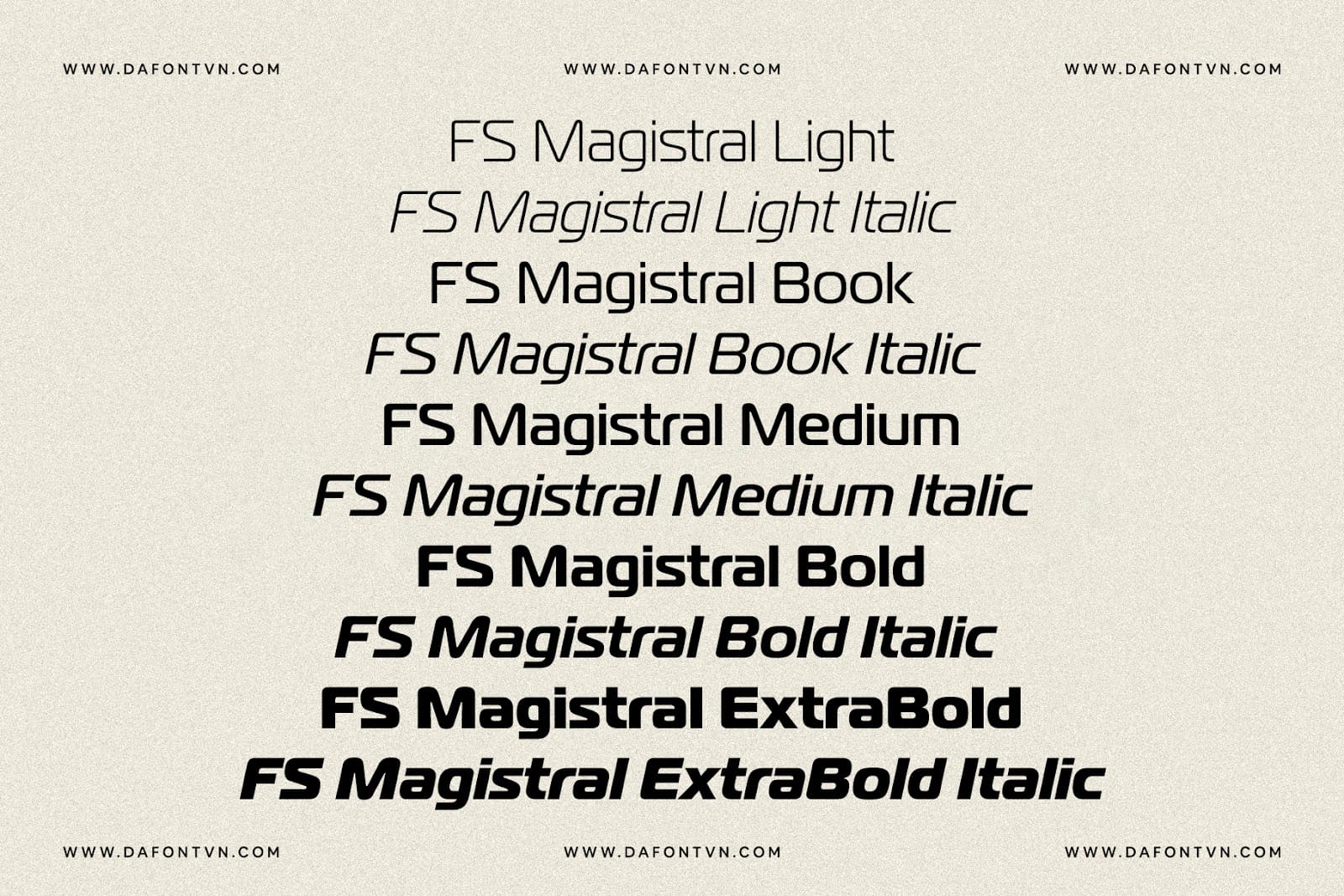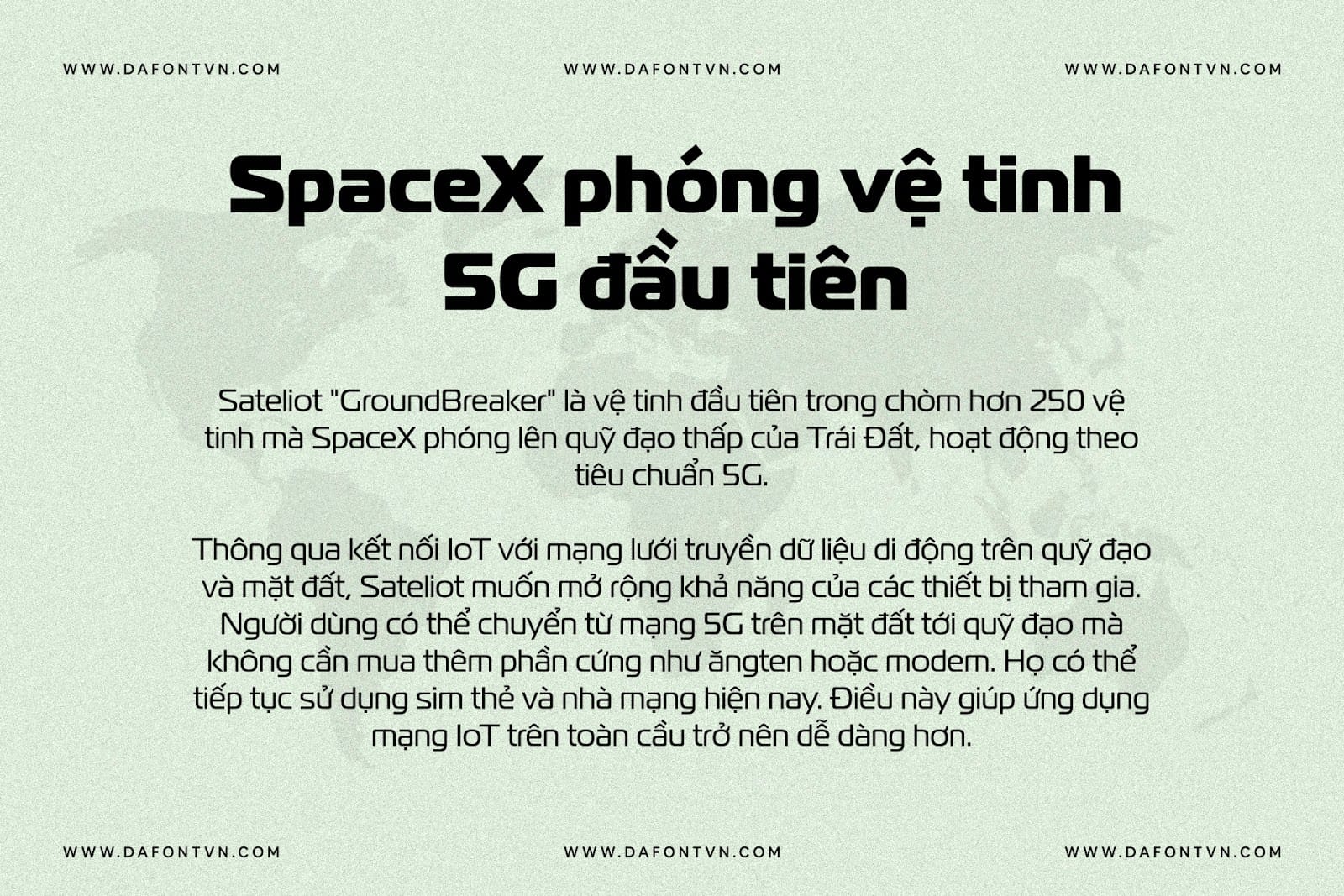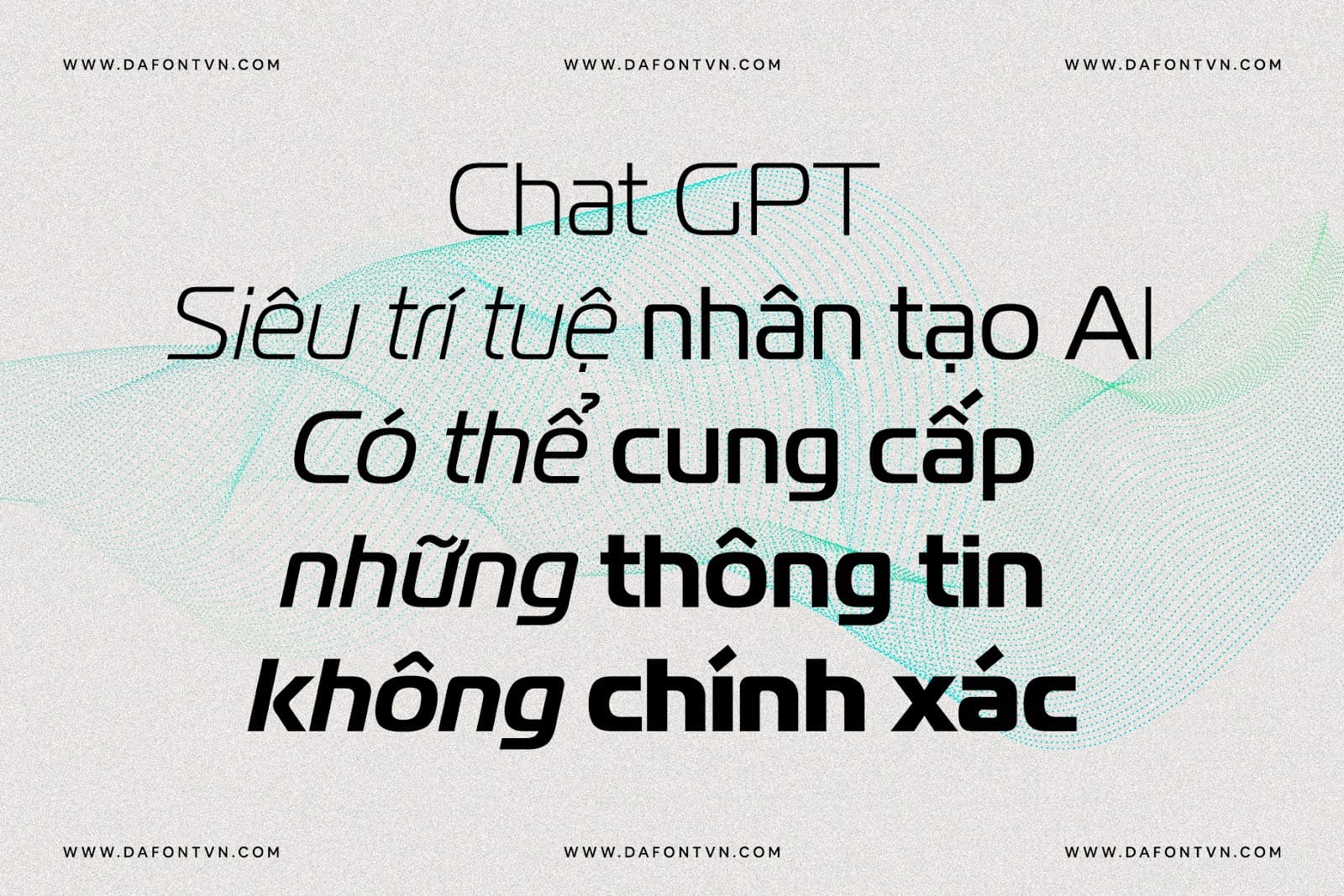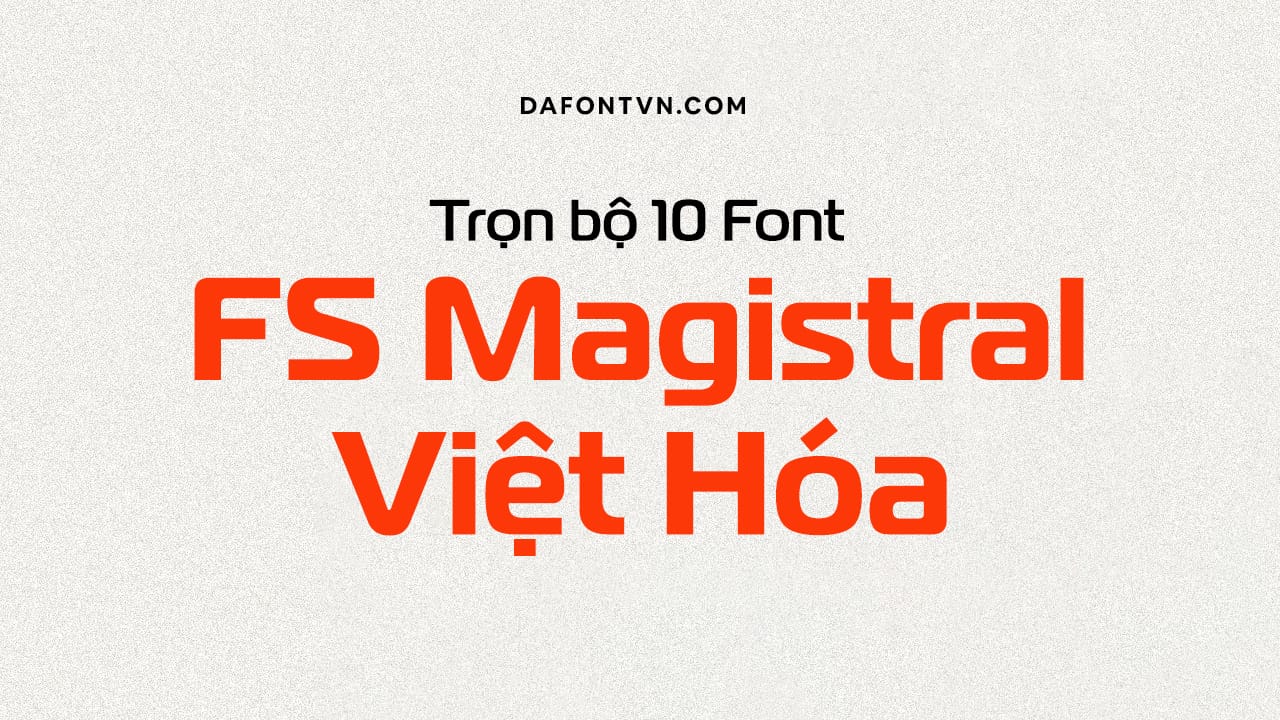
FS Magistral là bộ font được ra đời vào năm 2003. Magistral dựa trên tác phẩm nghệ thuật của nhà thiết kế đồ họa người Nga Andrey Kryukov (1923-1997). Phiên bản gốc đã được phát triển bởi Kryukov vào cuối thập kỷ 1960. Tỉ lệ và yếu tố thiết kế được lấy cảm hứng từ Eurostile (1962) của Aldo Novarese. Nó được thiết kế để sử dụng trong quảng cáo và kiểu chữ hiển thị. Năm 2009, Dmitry đã thêm các style mới, sửa lại các font cũ và bổ sung chúng với bộ ký tự mở rộng.
Đây là bộ font FS Magistral Việt hóa bao gồm 10 kiểu được việt hóa bởi phông chữ việt và bộ font này từng được Viettel sử dụng cho bộ nhận diện thương hiệu của mình.
Mặc dù bộ font này đã ra đời cách đây 20 năm tuy nhiên nó vẫn được sử dụng phổ biến, với các ký tự bo tròn đẹp mắt và hiển thị tốt ở mọi kích thước vì vậy mà Magistral cho đến ngày nay vẫn được sử dụng cho rất nhiều thiết kế.